ロゴのマイナーチェンジをきっかけにブランドの活性化に取り組む重要性
現代のビジネス環境はますます競争が激化しており、企業活動における露出媒体の理由づけは重要性を増しています。
企業の持つブランド価値を最大限に活用したいと考えておられる経営者の方も多いのではないでしょうか。
そこで、今回はロゴのマイナーチェンジについて探求し、そのアップデートの重要性に焦点を当てたいと思います。ロゴは企業のイメージを象徴し、顧客との結びつきを深める重要な要素です。マイナーチェンジによるアップデートは、ブランドの活性化に大いに寄与することができますので、ぜひ参考にしてみてください。
ロゴのマイナーチェンジによる変化・効果
ブランドアイデンティティの現代化
ロゴは企業のアイデンティティを表現するための重要なツールですが、時代の変化に伴い、顧客の嗜好やトレンドも変わっています。ロゴのマイナーチェンジを通じて、ブランドのイメージを現代的にアップデートすることで、顧客の関心を引きつけ、競争力を高めることができます。例えば、シンプルでモダンなデザインは近年の変化の特徴ですし、カラーパレットの見直しによるターゲット層への寄り添いを感じる変化などは、例えそれが小さな変化であったとしても、ブランドの印象をアップデートすることが可能です。
ブランドの差別化
競合他社との差別化は、成功を収める上で不可欠です。ロゴのマイナーチェンジは、ブランドのユニークな特徴や価値を際立たせる手段として活用できます。例えば、伝統的なロゴを現代的な要素でアップデートすることで、ブランドの歴史と進化を組み合わせることができます。このような差別化は、中小企業にとって顧客の注意を引き、競争相手との差を明確にする重要な戦略となり得ます。
変化することで保てるブランドの一貫性
変化なのに一貫性?と感じられたかもしれませんが。マイナーチェンジによる変化こそ一貫性を訴求する一手でもあります。ブランドの基本的な要素を保ちながらも、新しいアイデアや価値観を取り入れることができるマイナーチェンジによって、変わるところ・変わらぬところを明確化し、顧客に伝えることができます。少しずつ変わり柔軟に対応しながらも、変わらない姿勢。それに顧客は惹かれ、忠誠心を育みます。
コミュニケーションの活性化
ロゴは、ブランドとステークホルダーの間のコミュニケーションの重要な手段を担います。顧客ではなくステークホルダーと記したのには理由があります。ロゴは、マイナーチェンジを行うことで、ブランドが新たなストーリーを伝える機会を生みます。なぜ変えるのか、どう変えるのかといった思考の試行は、ロゴに触れるすべての人(従業員や経営者の家族など)に波及するのです。新しいロゴは、その掲載媒体を通じて、ステークホルダーとの対話を活発化させます。新しいロゴに興味を持ち、ブランドについての会話が広がることで、企業の知名度と関心を高めることができます。
実はetomojiロゴもマイナーチェンジをしました
etomojiのロゴは、代表の清川が独立するより前に存在していたロゴです。
Optimaというエレガントなフォントを参考にしつつ、一から作字しています。特に頭文字のeは、何度も推敲を重ね、完成まで酷く長い時間をかけて思い出があります。ベジェ曲線のフォルムを探るために、Illustratorで6400%ほどのズーム機能を使って、それの1pxを気にしながらひたすらライン取りをしていた当時には、狂気すら感じます。
インハウスデザイナー時代の個人創作をしていた頃からなので、2016年ごろでしょうか。7年以上変わらず使ってきたロゴを先月変更しました。さらに仲間との関係を強固なものとし、これまでの1人の腕で制作をしてきた個人から組織としての強さを持たせるために変更しました。太さを持たせ、より安定した形状に変えています。また、中央のmは、DNAを刻むというミッションのテーマ性を表現するため、部分的に切り書きのようなあしらいを入れました。
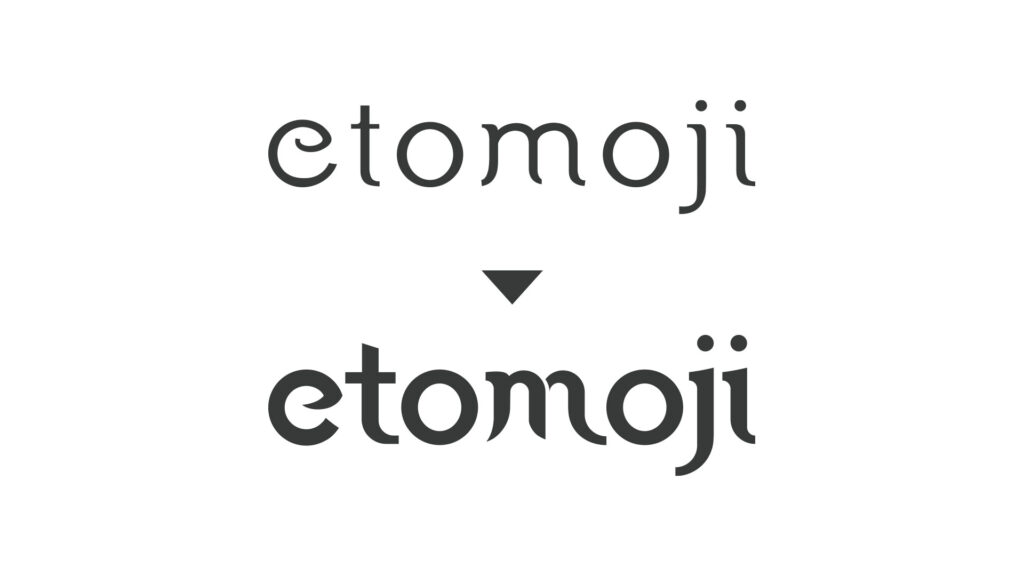
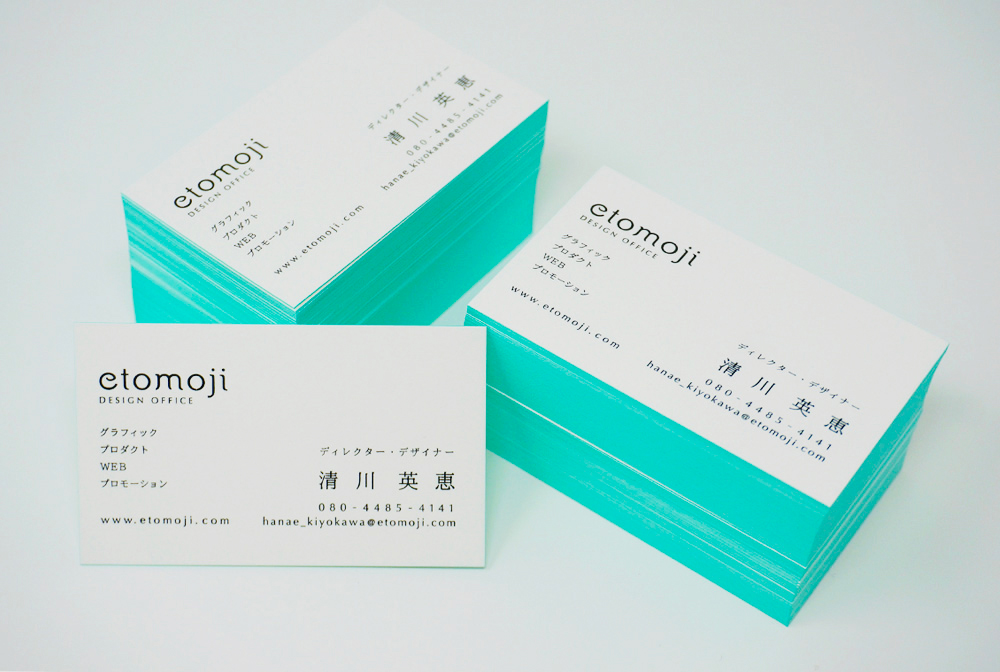
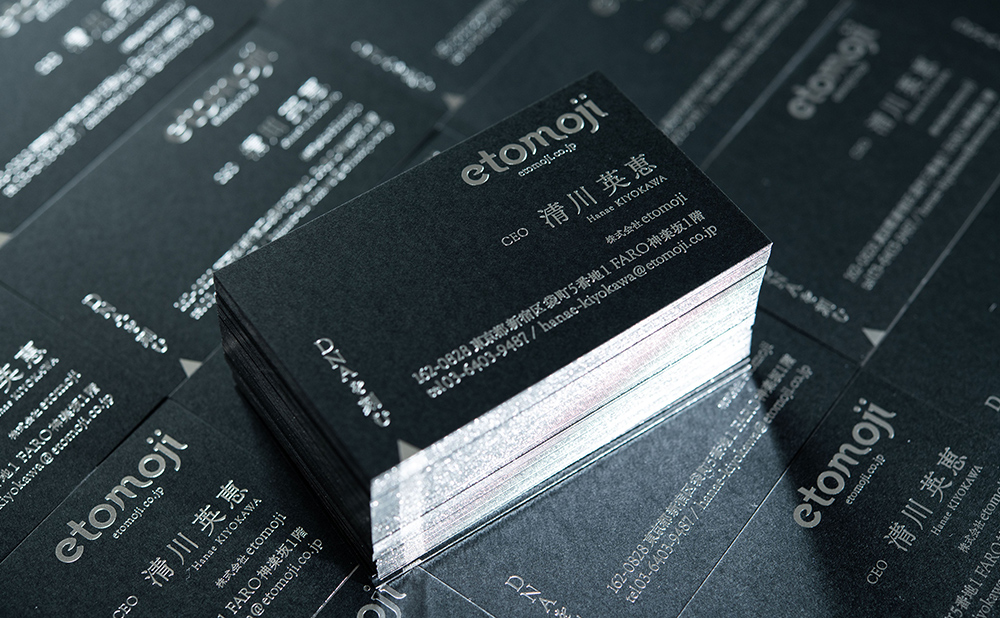
写真はロゴ変更前と変更後の名刺ですが、こうして比較していただくと、少し印象が変わったと感じられるのではないでしょうか。
ロゴは必ずしも形状から全てを変えなければならないものではないのですが、事業のポリシーに従って必要な時期に見直しをすることは、とても重要です。何を残して、何を残さないか。事業の棚卸しをするのと同じように、ロゴも数年に一度はぜひ見直しをしてみてくださいね。